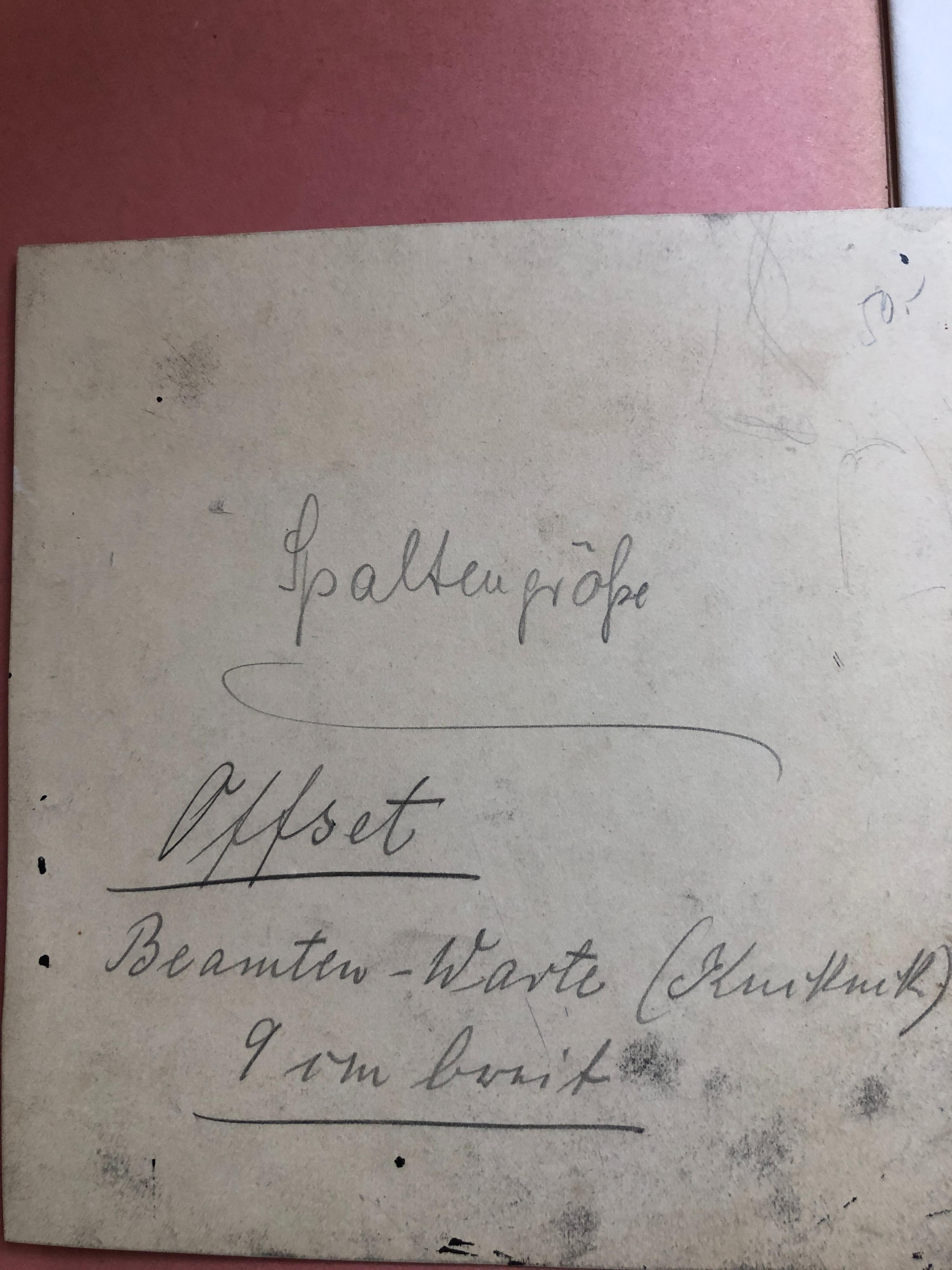
Beamten-Warte. Hilfe beim Entziffern des Wortes in Klammern
Hallo. Welch tolles Forum! ich bin sehr erfreut, dass es das gibt. Ich kann ein Wort nicht entziffern (siehe Foto) und zwar das Wort in Klammern. Ich sehe Spaltengröße oder Spaltenprobe?, Offset, Beamten - Warte und 9 cm breit, aber das Wort in Klammern erkenne ich partout nicht.
Ich lese den ersten Buchstaben automatisch als großes K. Aber wenn ich mir die Buchstaben z.b. der Kurrentschrift anschaue, dann sieht das große K irgendwie anders aus?! Aber vielleicht habe ich auch noch nicht alle Varianten gefunden?
Auf der Vorderseite ist übrigens ein Bild u.a. mit zwei  Damen im Vordergrund zu sehen. Wahrscheinlich französisch? mit P. "signiert". Aber das weiss ich auch nicht zuzuordnen.
Beim Wort in Klammern hätte ich sofort auf Kuckuck getippt. Unsere Vorfahren haben aber zumeist darauf geachtet, ein kleines u mit einem entsprechenden Kringel darüber zu kennzeichnen. Eine andere plausible Lesart habe ich aber nicht parat.
Die Beamten-Warte war von 1914 bis 1922 eine Beilage zur Berliner Tageszeitung Deutsche Warte. Das Wort könnte also ein Kolumnentitel oder ein Autorname des zu illustrieren Artikels sein.
In der SBB ist die Zeitung auf Mikrofilm einsehbar. Von der Mode her, könnte es sinnvoll sein, bei den letzten Exemplaren zu beginnen.
Unsere Vorfahren haben aber zumeist darauf geachtet,
Nicht immer und überall, z.B. wenn das Wort auch so erkennbar wäre*, darum bin ich durchaus bei dir und dem Kuckuck. Zumal auch lateinische Buchstaben eingestreut sind.
*) So hat es zumindest meine Großmutter gehandhabt und es ist auch auf einigen Postkarten etc. der Familie ähnlich zu sehen. Schrift ist neben allen Regeln eben auch immer sehr individuell …